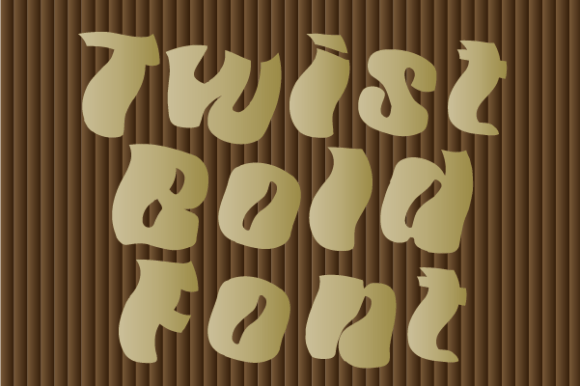
Twist Bold
適切なデザイン要素を見つけるのは難しい場合がありますが、Twist Boldは作品を即座に引き立てる優れたコレクションを提供します。
POD(オンデマンド印刷)製品、結婚式の招待状、またはソーシャルメディアのグラフィックを作成している場合でも、Twist Boldは理想的です。